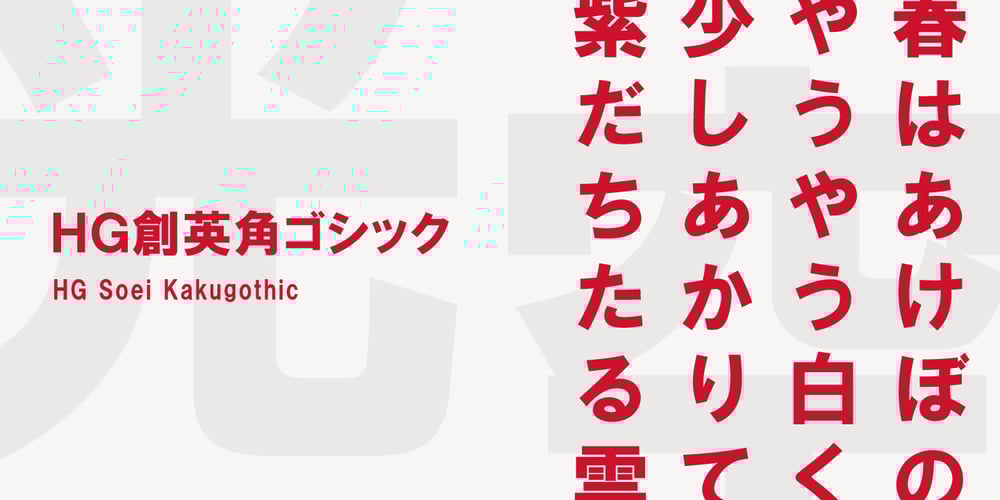
HG Soei Kakugothic
HG Soei Kakugothic Font Family was designed by published by RICOH. HG Soei Kakugothic contains 1 styles and family package options. HG創英角ゴシックLは、極細のゴシック体で、創英企画によるデザインです。シンプルな線で構成された現代的なゴシック体で、仮名が大きめに作られていて、全体的な印象はとても明るくカジュアルです。HG創英角ゴシックUBは、極太のゴシック体で、水本恵子氏のデザインです。仮名はHG創英角ゴシックLと比較すると小さめに設計されていて、現代的でありながらも、フォーマルさも合わせもっています。